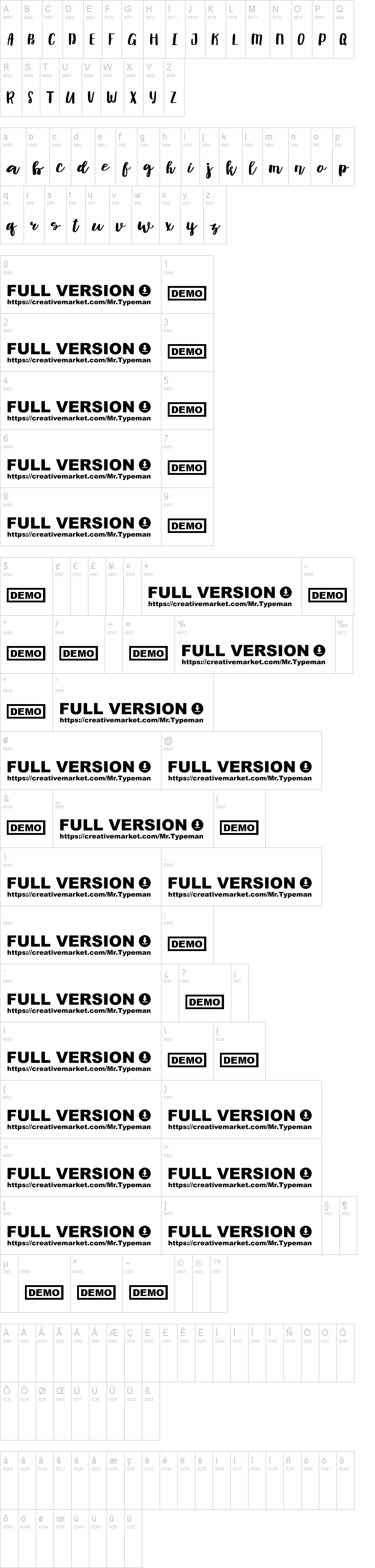
Muscat
Muscat 字体是一款具有强大表现力的多功能英文字体,它是由新西兰设计师Paul Barnes和Christian Schwartz于2009年设计的。Muscat字体具有独特的风格,它的字形设计简洁、大方,具有丰富的表现力,可以满足不同的设计需求。它的设计深受18世纪英国绘画家William Hogarth的影响,以及19世纪的英国出版物的字体设计。Muscat字体可以用于许多不同的应用,如书籍封面、广告、网页设计等。
Muscat是一款非常不错的手写艺术字体,具有很好的视觉感,适合于文化类的宣传设计、商业类品牌的广告和产品包装设计以及个性化文字排版等较多场景。